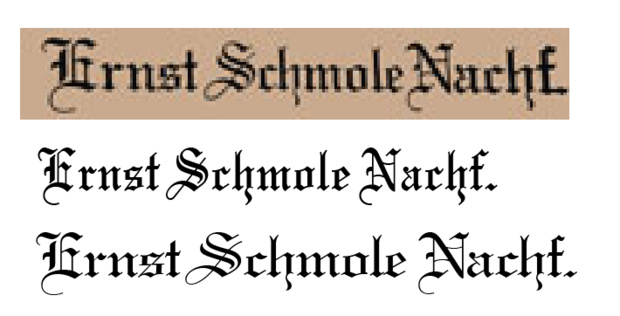
gesucht wird der obere, gepixelte font.
ich dachte sofort an corel – die beiden die ich gefunden habe sind
Mariage und Wedding Text (Lincoln)
kommen beide jedoch nicht hin.
jemand ’en idee?
Ist das denn überhaupt gesetzt oder wurde da evtl. das Bild von der Fassade übernommen?
Irgendeine Vorlage werden sie gehabt haben, das ist schon klar ;-) Mir fiel nur auf dass sowohl in dem kleinen Logo als auch auf der Fassade das f zu dick geraten ist, daher dachte ich dass das im www evtl. einem Bild der Fassade entsprang.
Die Schrift am Foto von der Fassade läuft breiter als auf der Abbildung oben und ist hier unter Old Gondor zu finden, diese ist m. E. ident mit der von Dir erwähnten Wedding Text.
Das Bild wurde nicht exakt frontal aufgenommen, daher werden die Buchstaben von links nach rechts immer fetter.
… daher werden die Buchstaben von links nach rechts immer fetter.
Der Sprung vom h zum f ist aber schon eklatant.
Sehe das auch so.
Aber da dürfte die niedrige Auflösung des Bildes ebenfalls eine Rolle spielen.
könnte sein. ich bin mir allerdings noch nicht ganz sicher, das o sieht zumindest
auf dem screenshot etwas anders aus, könnte aber wirklich an der niedrigen auflösung liegen.
wenn man die fonts auf 80 % verzerrt scheint es sogar fast hinzukommen, ich glaub das reicht mir.